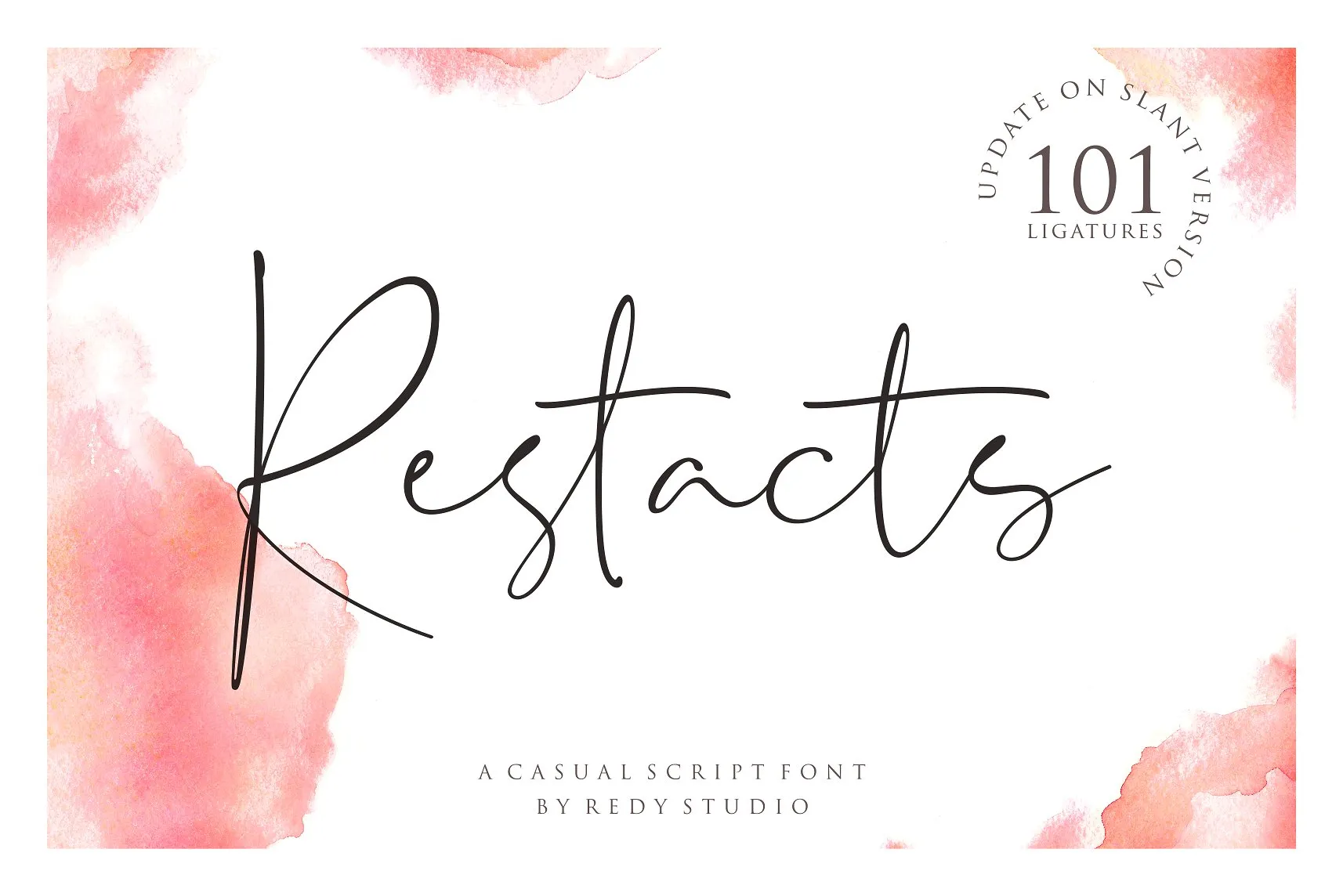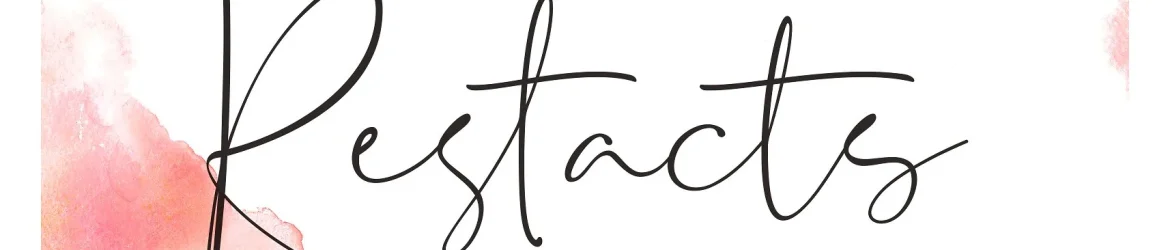
Restacts Script Font – Download Grátis
Através do Restacts Font da RedyStudio você encontrará duas variações de uma script casual e elegante, perfeitas para diversos projetos de design. A primeira opção, a Restacts Script, é mais feminina e informal, enquanto a segunda, mais elegante e com traços mais marcados, oferece um toque diferenciado em qualquer projeto. Os designs podem variar desde marcações criativas e profissionais para invitações de casamento, imagens fotográficas e até mesmo redes sociais e logotipos. O Restacts é uma fonte script perfeita para adicionar um toque sofisticado a seus projetos sem parecer exagerada. Experimente o preview que acompanha a fonte para ver como ela se destaca em diferentes estilos de design.